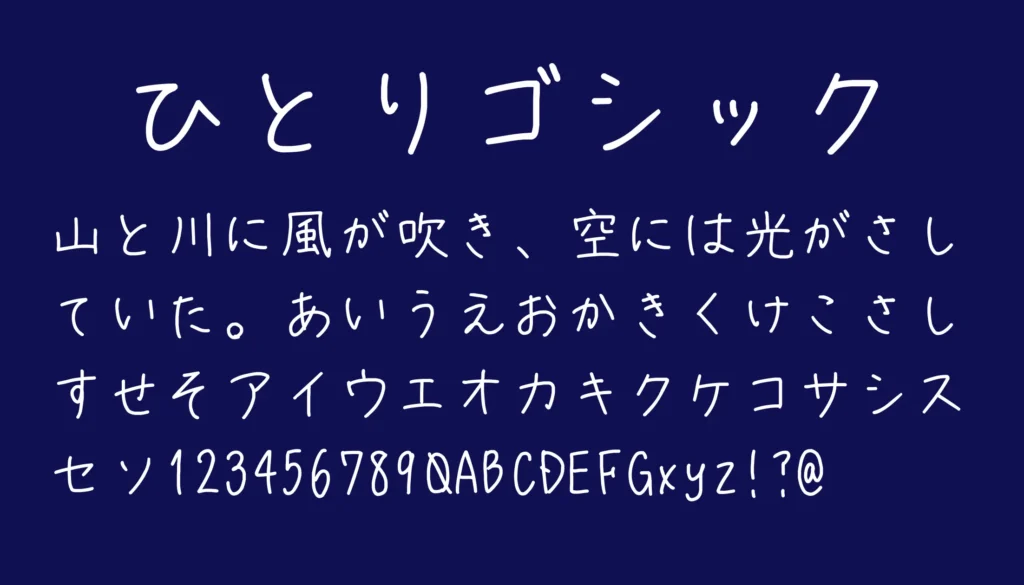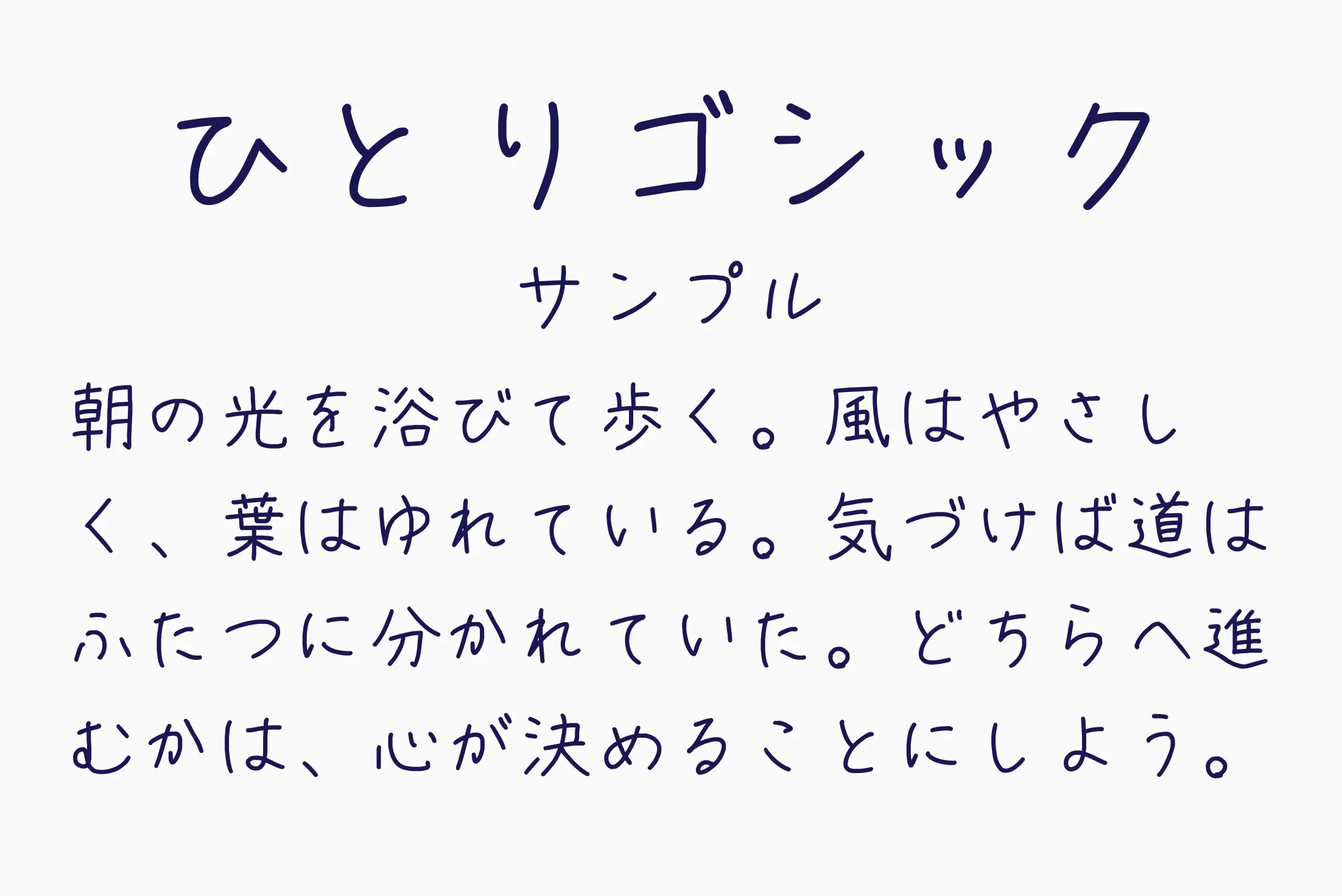
ゆるく手書きしたようなラフさと、細めゴシックの読みやすさを両立した手書きフォント。ガタつきや不均一さをあえて残していて、「ノートにさらっと書いた文字」みたいな自然体の空気感があります。かわいすぎず、かっこよすぎず、静かな温度感があるので、エッセイ風デザイン・Vlogテロップ・日常系YouTube・同人誌・ZINE・カフェ系投稿などとかなり相性良め。クセはあるけど視認性はちゃんとあるので、見出しだけじゃなく本文寄りにも使いやすいタイプです。
ひとりゴシック